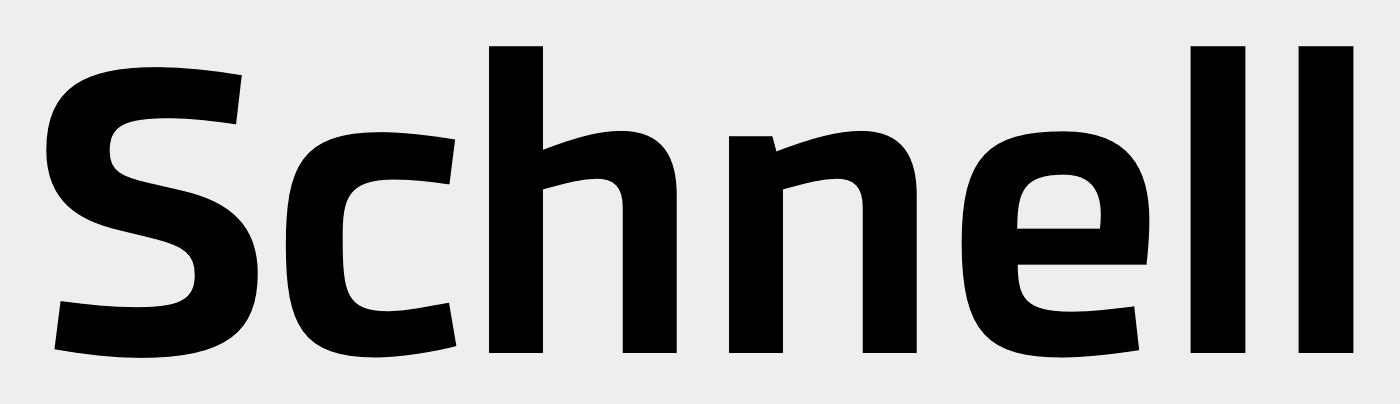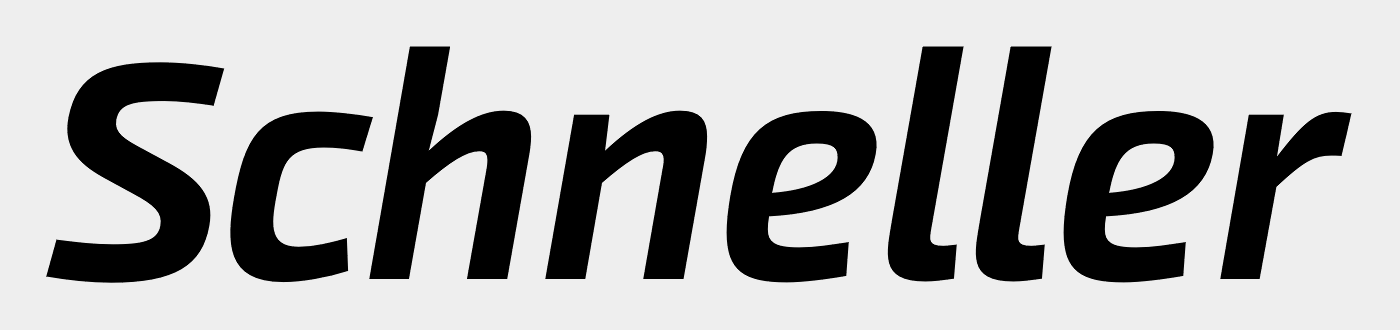
ich finde diese Schift nicht (Drucklufttechnik)
Ich würde sagen, die Myriad ist nicht nur ähnlich … :-)
Allerdings hat die Druckluft wohl für etwas mehr Neigung gesorgt …
Sozusagen eine oblique-italic... Gibt es eigentlich Schriften mit mehreren Kursivgraden?
Die Neigung erscheint nicht durchgehend gleich, schon mal an ein ("perspektivisch verzerrtes") Foto gedacht?
Ja, so etwas gibt es: beispielsweise die »Akceler« von Andrej Dieneš.
Auch etwa Underwares Auto Pro und Peter Matthias Noordzijs Caecilia Sans lassen die Wahl zwischen verschiedenen Nuancen von Kursiven. Hier ändert sich aber in erster Linie der Aufbau der Glyphen – weniger sind es abgestufte Schrägegerade mit derselben Glyphenkonstruktion.